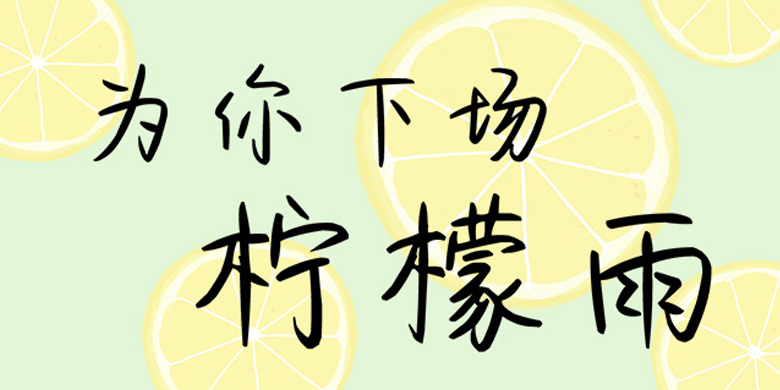
方正手迹-为你下场柠檬雨
字体品牌: 方正手迹 设计师:宋昱东 字体分类:创意书写 字体属性:精品字 字符集:简繁扩展(GBK) 发布时间: 2020
为你下场柠檬雨是一款行笔流畅的手写体。该字体既有行书飘逸潇洒的一面,又有圆润可爱的一面感觉。所以适用于文艺类和可爱类的书刊、品牌广告和产品包装设计,以及社交网络的个性化用字。